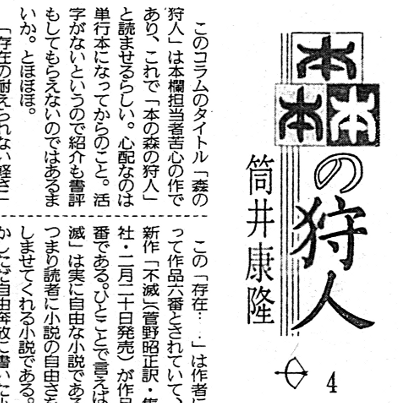
本の森をたずねて
先日書いた『くおんの
』*1の
という漢字(以下、本×3と表記)について、続き。
id:funaki_naoto さんの記事「本の森」を読んで、この漢字が筒井康隆『本の森の狩人』*2でも使われているということを知った。で、『本の森の狩人』は読売新聞朝刊の読書欄に連載していたものだというので、活字の本×3がないかと思って縮刷版を見てみた。
本×3 @読売新聞
下の画像は、1992年1月27日付け朝刊の7面に掲載された「本×3の狩人」(第4回)の記事。
*3
題字の本×3は篆書風のロゴになっている。また本文の1行目には、明朝体になった本×3が使われている。この連載は1年間(全51回)続くが、連載本文中に活字の本×3が現れるのは、残念ながらこの1箇所のみのようだ。
ただ、活字の本×3が使われている箇所は、実はもう一つある*4。最終回が掲載された1992年12月21日の紙面で、9面の「おことわり」にこの文字が見える。
記事にあるように1993年1月4日からは「本×3の散策」という連載が開始され、これは1995年5月1日(第118回)まで続いている。この連載の題字には「本×3の狩人」の題字を流用したもの(「狩人」が「散策」になっただけ*5)が使われていた。こちらの本文については調べていないが、雰囲気としては本×3は出てきそうにない。
本×3 @本の森の狩人
funaki_naoto さんが記事に書いていたのが、この『本の森の狩人』。タイトルについて、「はじめに」から引用すると、
これは一九九二年(平成四年)、一年間にわたって『讀賣新聞』朝刊の読書欄に連載したものである。そもそもは「
筒井康隆『本の森の狩人』岩波書店、1993年、p. i, iiの狩人」というタイトルだったが、文中にもあるように本にする際造字であっては各方面に迷惑をかけそうなので、このように改めた。
……
文中にも出てくる讀賣新聞社の最初の担当者・鵜飼哲夫氏には前出のタイトルのアイディアその他いろいろと貴重なご意見を戴いた。
とあるので、この鵜飼哲夫氏が本×3という漢字を創り出したようだ。この本で本×3が登場するのは、上に引用した部分と、第4回の本文(最初の画像の部分。p. 14)の2箇所だけ。
『くおんの森』と『本の森の狩人』
『くおんの森』の作者・釣巻和氏の日記には くおんの
と書かれている*6ので、おそらく「本×3の狩人」の本×3とは独立に創作されたものだろう。「本×3の狩人」の連載当時は、作者はまだ5,6歳だし*7。字形が同じで(たぶん*8)意味も近いので、暗合といって良いのかもしれない。ただ、『くおんの森』の「本×3」は、「本の森」ではなく「もり」と読むようなので注意。
(←造語)です。